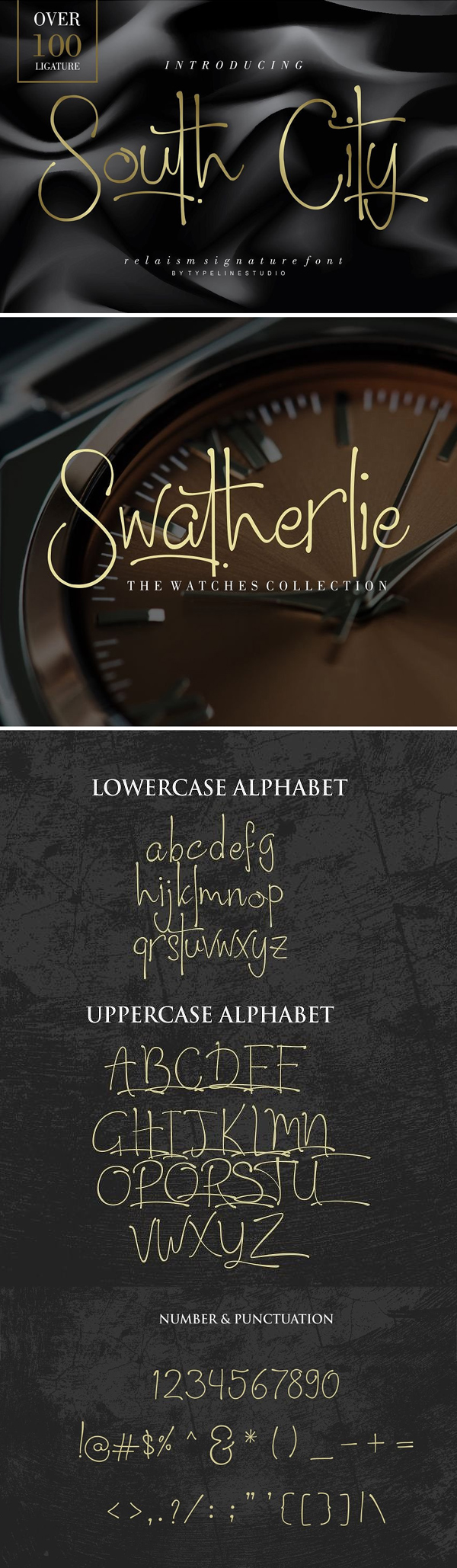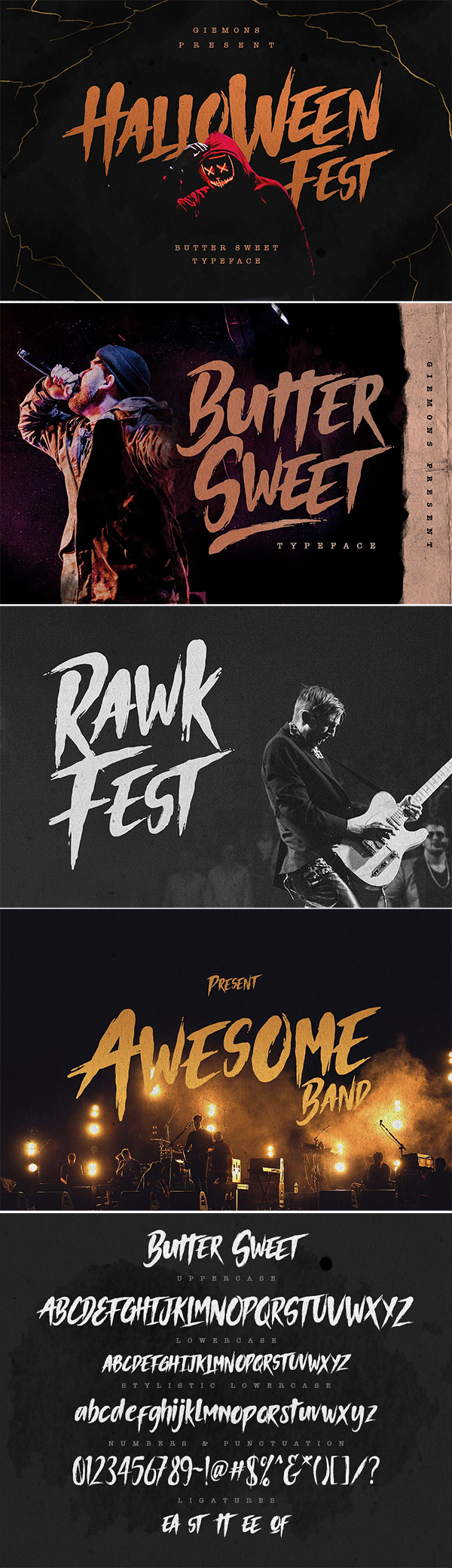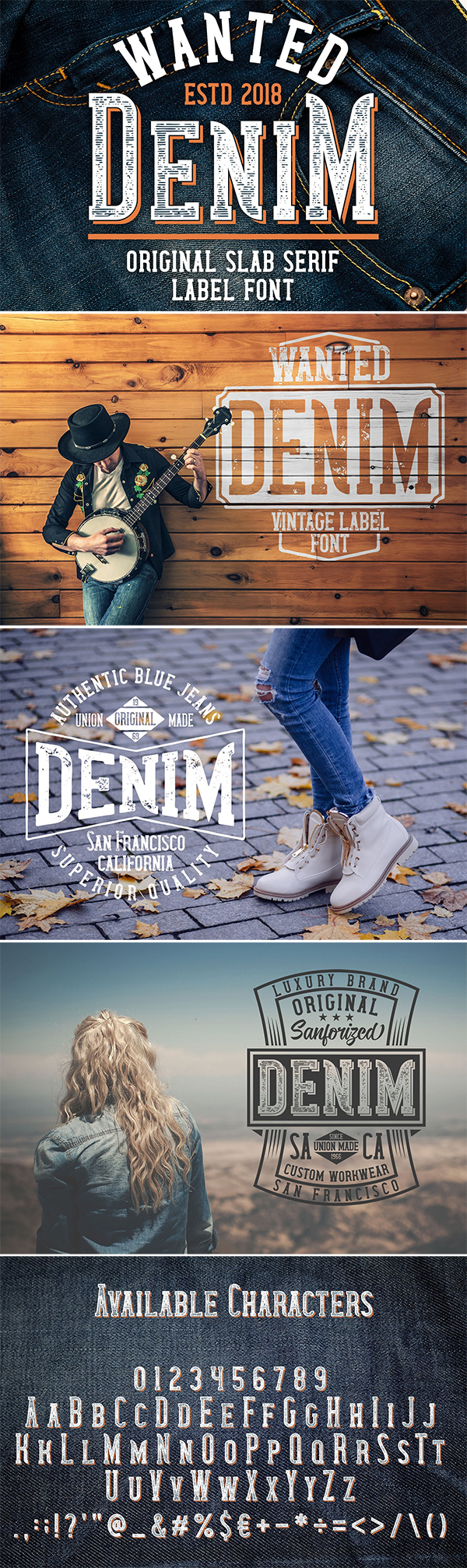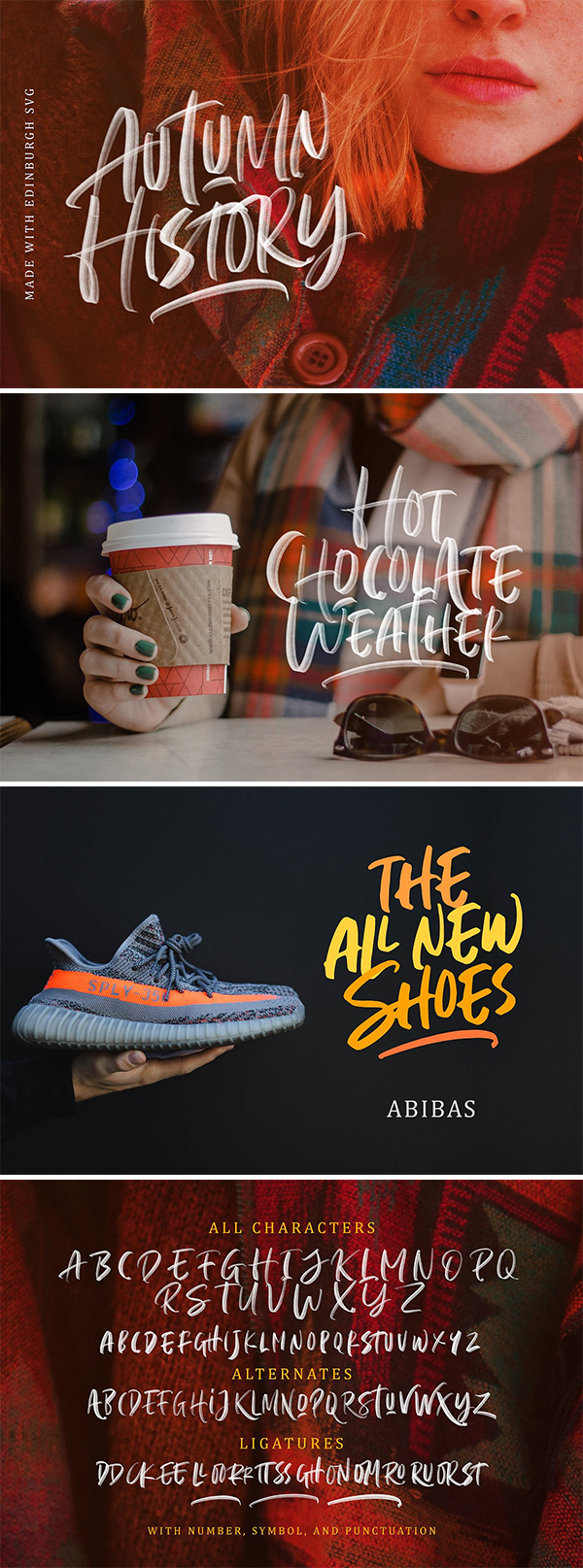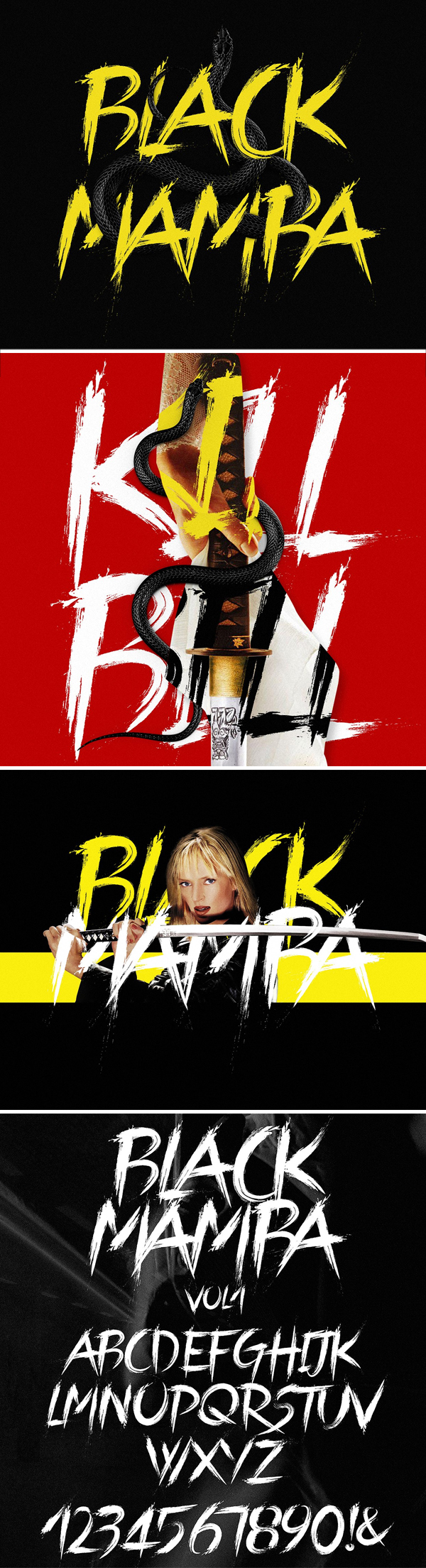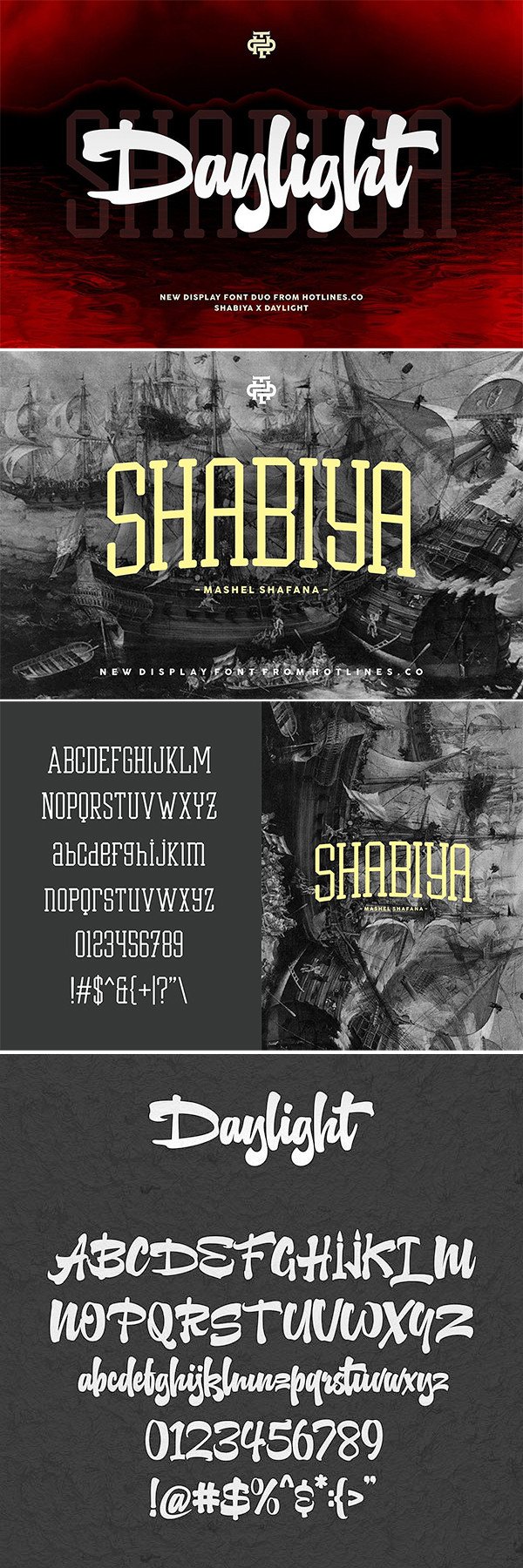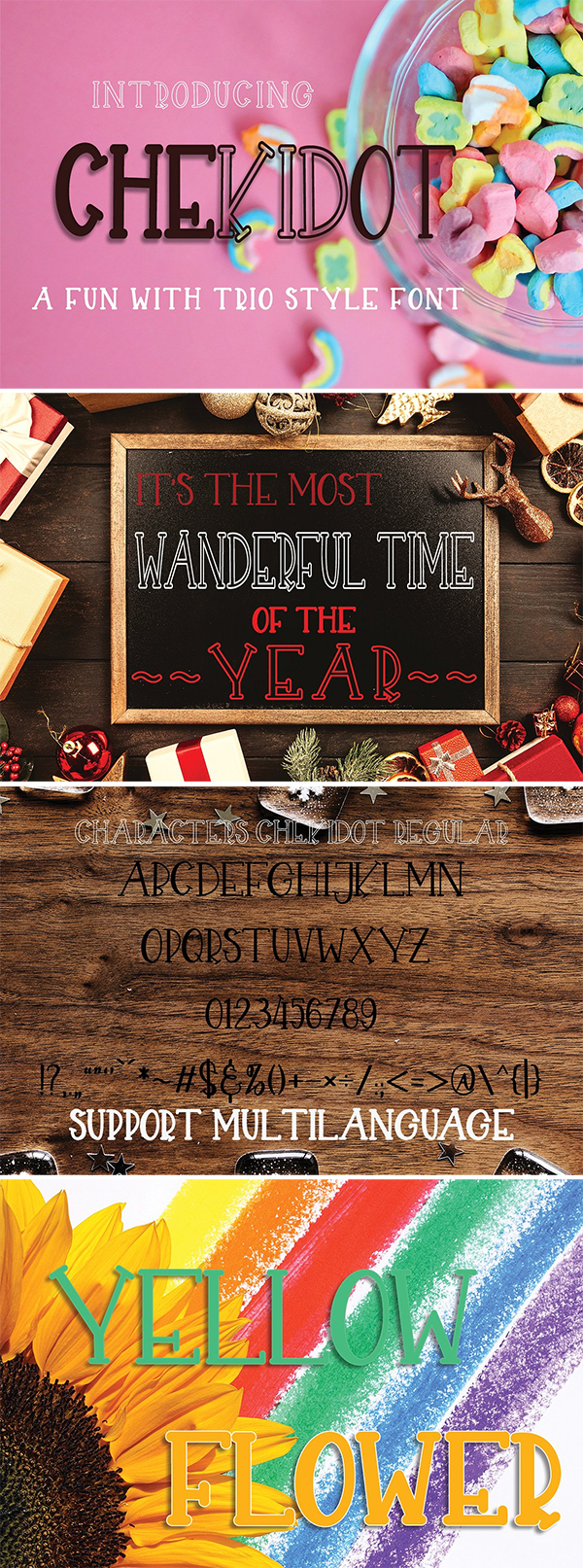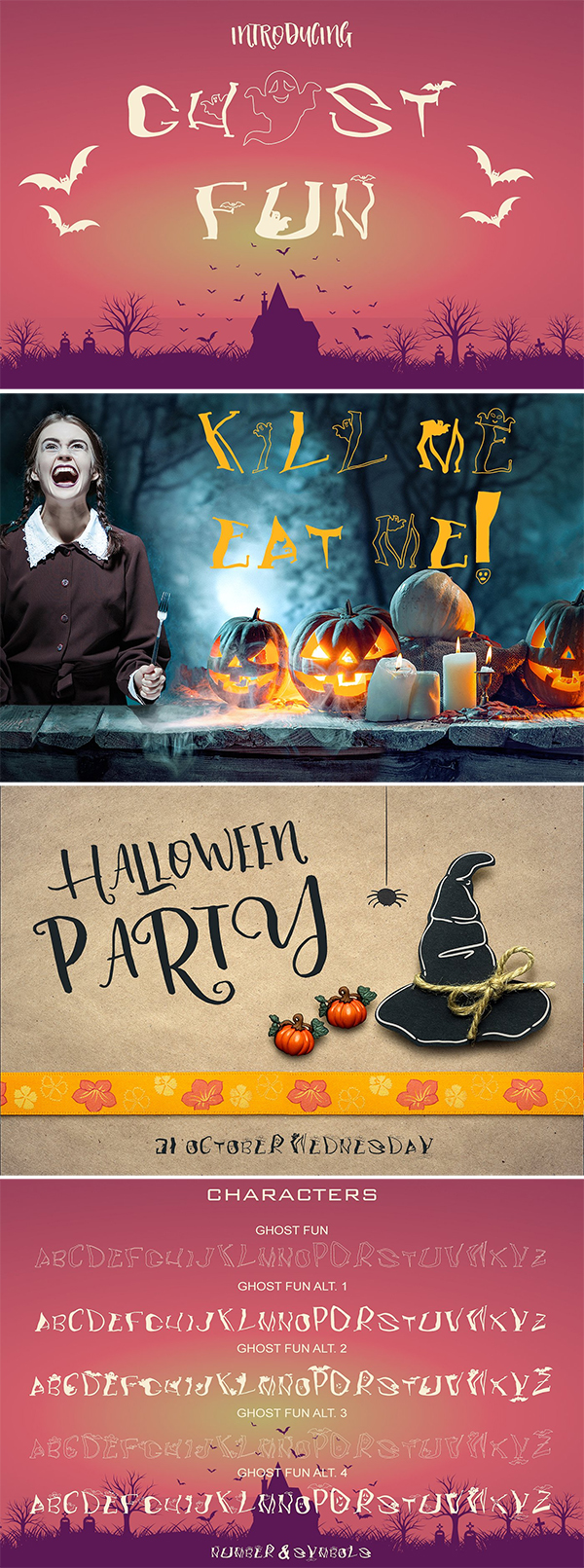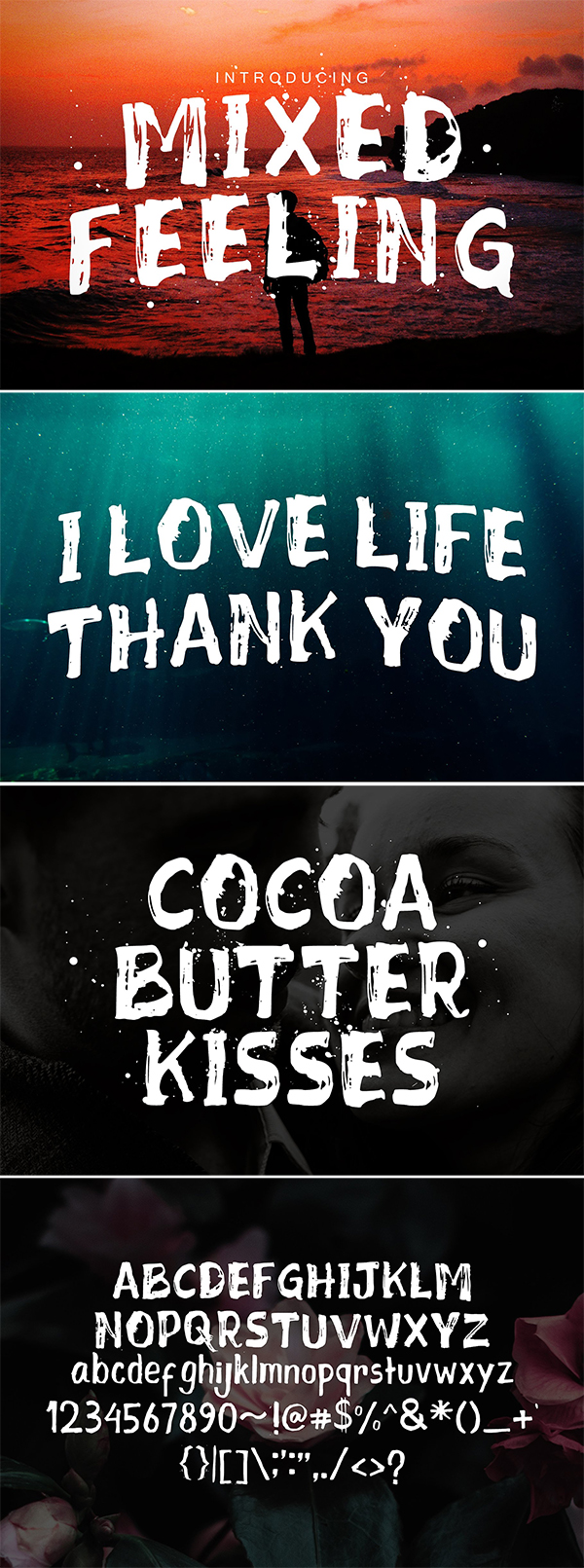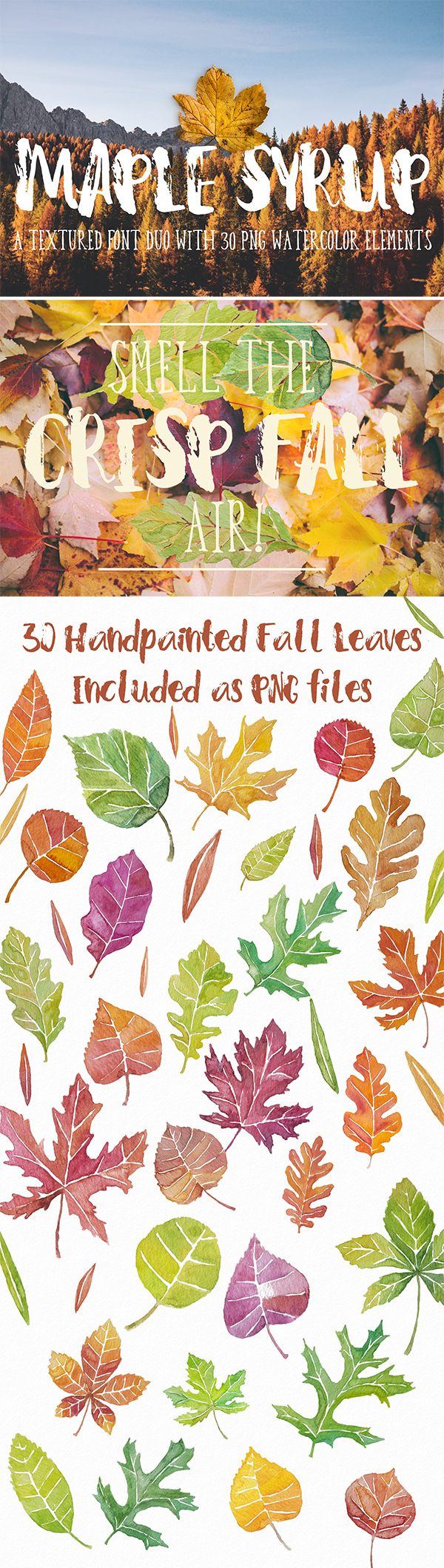
รูปแบบตัวอักษร และแบบอักษรที่ดีที่สุดสำหรับนักออกแบบ แบบอักษรที่รวมแบบอักษรสคริปต์, แบบอักษรที่เขียนด้วยลายมือแปรง, แบบอักษรวินเทจ และแบบอักษรที่แสดงผลที่สามารถเป็นที่สมบูรณ์แบบสำหรับการสร้างตราสินค้าโลโก้, การ์ดอวยพร, เครื่องเขียนงานแต่งงาน, คำพูดการพิมพ์หนังสือปกหัวเว็บไซต์, ใบปลิว, เสื้อผ้า, ออกแบบบรรจุภัณฑ์ และอื่นๆ แบบอักษรที่ออกแบบอย่างมืออาชีพ สามารถปรับปรุงการออกแบบของคุณได้อย่างมีนัยสำคัญ คือ
1. South City Realism Script
แรงบันดาลใจของตัวอักษร South City เป็นลายเซ็นที่เขียนด้วยลายมือ และตัวอักษรที่สง่างาม
1. Dialova – Beautiful Calligraphy
การเอียง และการสลับที่งดงาม แบบอักษรนี้ยังใช้งานง่าย และมีสัมผัสของความสง่างาม และความทันสมัยสำหรับการออกแบบ หรือการสร้างตราสินค้าของคุณ สามารถใช้เพื่อวัตถุประสงค์ต่างๆ ได้
1. Butter Sweet Typeface
สามารถทำให้ข้อความในการออกแบบของคุณง่ายขึ้น ใช้สำหรับการแสดงผลที่ยอดเยี่ยมการติดฉลากเสื้อผ้า screen ภาพยนตร์โปสเตอร์ ชื่อภาพยนตร์ ปกอัลบั้มโลโก้ และอีกมากมาย
1. Wanted Denim Layered Font
แบบอักษรนี้ได้รับแรงบันดาลใจจากแบบอักษรพื้นแผ่นป้ายคลาสสิกจากป้ายผ้ายีนส์ และโลโก้
1. Fairly Certain – Handmade Font
1. BlackBeast Typeface
เป็นตัวอักษรที่เขียนด้วยลายมือแบบ dapper พร้อมกับเสน่ห์ส่วนตัว ด้วยลายเส้นที่ยาก และสไตล์ที่เป็นเอกลักษณ์ Black Beast
1. Sandy Hand Letter ed Font
1. Tinsel Tangle Font
ใช้ตัวพิมพ์ใหญ่ หรือตัวพิมพ์เล็กทั้งหมด หรือผสมกัน! Tinsel Tangle เป็นฟอนต์อเนกประสงค์ที่คุณสามารถใช้ได้กับทุกโปรเจค
1. Butcher Killer Display Font
Butcher เป็นแบบอักษร serif โบราณ / สมัยใหม่ที่สามารถใช้ในงานโครงการจำนวนมาก มีมาในสองรูปแบบปกติ และเบา
1. Edinburgh – SVG Font
1. Black Mamba Font
1. Daylight x Shabiya Display Font
Daylight x Shabiya เป็นตัวอักษรคู่ใหม่จาก Hotlines.co ชุดอักขระที่ให้ความรู้สึกหรูหรา หากต้องการสร้างการผสมผสานที่สวยงามเพียงผสมตัวพิมพ์ใหญ่ และตัวพิมพ์เล็กแล้วผสมกับสัญลักษณ์ทางเลือก Daylight x Shabiya insfire จากสไตล์กราฟฟิตี และสไตล์ฮิปฮอป
1. Instant Sinner Display Font
แรงบันดาลใจจาก Sci-Fi โบราณ และการโฆษณาชวนเชื่อสยองขวัญ Instant Sinner จะทำให้คุณตกใจ
1. Paper Snow Font
1. Multicolored Neon Display Font
แบบอักษรเวกเตอร์แสงนีออนหลากสีสำหรับ Adobe Illustrator คุณสามารถใช้มันสำหรับการออกแบบของคุณสร้างชื่อเรื่องในโหมด RGB
1. Chekidot Trio Style Font
1. Fun Play Day Display Font
แบบอักษรนี้เหมาะสำหรับสร้างแบรนด์ สร้างโลโก้ หรือกรอบที่สวยงาม หรือเพียงใช้กับธุรกิจขนาดเล็กของคุณ ปกหนังสือเครื่องเขียน การตลาดบล็อก นิตยสาร และอื่นๆ
1. Rambutan Playful Font
ผสมและจับคู่ตัวพิมพ์ใหญ่ และตัวพิมพ์เล็ก เพื่อสร้างการออกแบบที่ไม่ซ้ำกันทุกครั้งที่คุณใช้
1. Blaza Display Font
1. Acres Sweet Font
เป็นตัวอักษรที่มีความหนา และข้น ซึ่งมีการออกแบบที่ได้แรงบันดาลใจมาจากต่างประเทศ สามารถออกแบบป๊อปอัพวันหยุด เทศกาล หรือสัมผัสสบายๆ
1. Ghost Fun Font Collection
Ghost Fun Font Collection เป็นเหมือนลายเซ็นในขณะที่คุณพิมพ์ แสดงให้เห็นถึงศิลปะการทำงานด้วยมือ
1. Mixed Feeling Font
ขอแนะนำตัวอักษรแบบผสมความรู้สึกตัวอักษรหยาบจากการใช้แปรงจริง ที่วาดด้วยมือด้วยความหนา และความยุ่ง คุณสามารถใช้มันสำหรับโซเชียลมีเดียได้
1. Play Glyphs Handmade Font
เหมาะสำหรับโลโก้แท็กชื่อคำพูดเขียนด้วยลายมือ บรรจุภัณฑ์ ผลิตภัณฑ์สินค้าโซเชียลมีเดีย และอื่นๆ มีชุดของตัวอักษรตัวพิมพ์เล็ก และตัวพิมพ์ใหญ่เต็มเครื่องหมายต่างๆ
1. Artomoro Handmade Font
Artomoro เป็นตัวอักษรงานฝีมือตามธรรมชาติ Artomoro เหมาะอย่างยิ่งสำหรับโลโก้ โปสเตอร์
1. Stanffords Font
สแตนฟอร์ดทำให้เกิดจิตวิญญาณของตัวอักษรพู่กันโบราณที่มีความทันสมัย คุณสมบัติเหล่านี้ทำให้สแตนฟอร์ดส์ดูสบายๆ เป็นกันเอง และทำด้วยมือ
1. Maple Syrup Fall Font Pack
แบบอักษรพู่กันใหม่ล่าสุด Maple Syrup ตัวอักษรที่มีพื้นผิว มาพร้อมกับใบไม้ร่วงที่วาดด้วยมือ สีน้ำ 30 ใบ และตัวอักษรแบบวาดด้วยมือโดยใช้ต้นสน
1. Quick Dream Script Font
Quick Dream เป็นตัวอักษร handlettering ที่สร้างขึ้นอย่างประณีต เป็นตัวอักษรที่สวยงามที่ผู้คนต้องการ
1. Jolly Christmas Font
1. Hillpark Script Font
1. Nebbulla – Font Duo
ใช้สำหรับการออกแบบทุกประเภท เช่น การสร้างแบรนด์ โลโก้ การออกแบบงานแต่งงาน โพสต์สื่อสังคมออนไลน์ โฆษณา
1. Realvish Script Font
เป็นฟอนต์สคริปต์ที่เขียนด้วยลายมือ โดยอิงตามการแสดงออกของรูปแบบลายเซ็นที่ไหลได้อย่างอิสระเป็นมิตร และเป็นธรรมชาติ
1. Shoot SVG Font
ยิงเป็นตัวอักษรที่ทำด้วยเนื้อน้ำมัน ระดับความแม่นยำในแบบอักษรนี้คมชัดมาก เหมือนกับเราวาดสีน้ำมันด้วยแปรง
1. Squick / All Family Font
1. Belymon Script Font
ไม่เหมือนใครด้วยการสัมผัสแบบคลาสสิก และอ่านได้อย่างรวดเร็ว เหมาะอย่างยิ่งสำหรับคุณที่ต้องการแบบตัวอักษร
1. Snug Sweater – Font Duo
1. Pecorino Font
1. Fantiyella Script Font
รูปแบบการประดิษฐ์ตัวอักษรทำด้วยมือ, ตัวอักษรพิมพ์ด้วยการเต้นรำขั้นพื้นฐานสัมผัสคลาสสิก และสง่างาม สามารถใช้เพื่อวัตถุประสงค์ต่างๆ